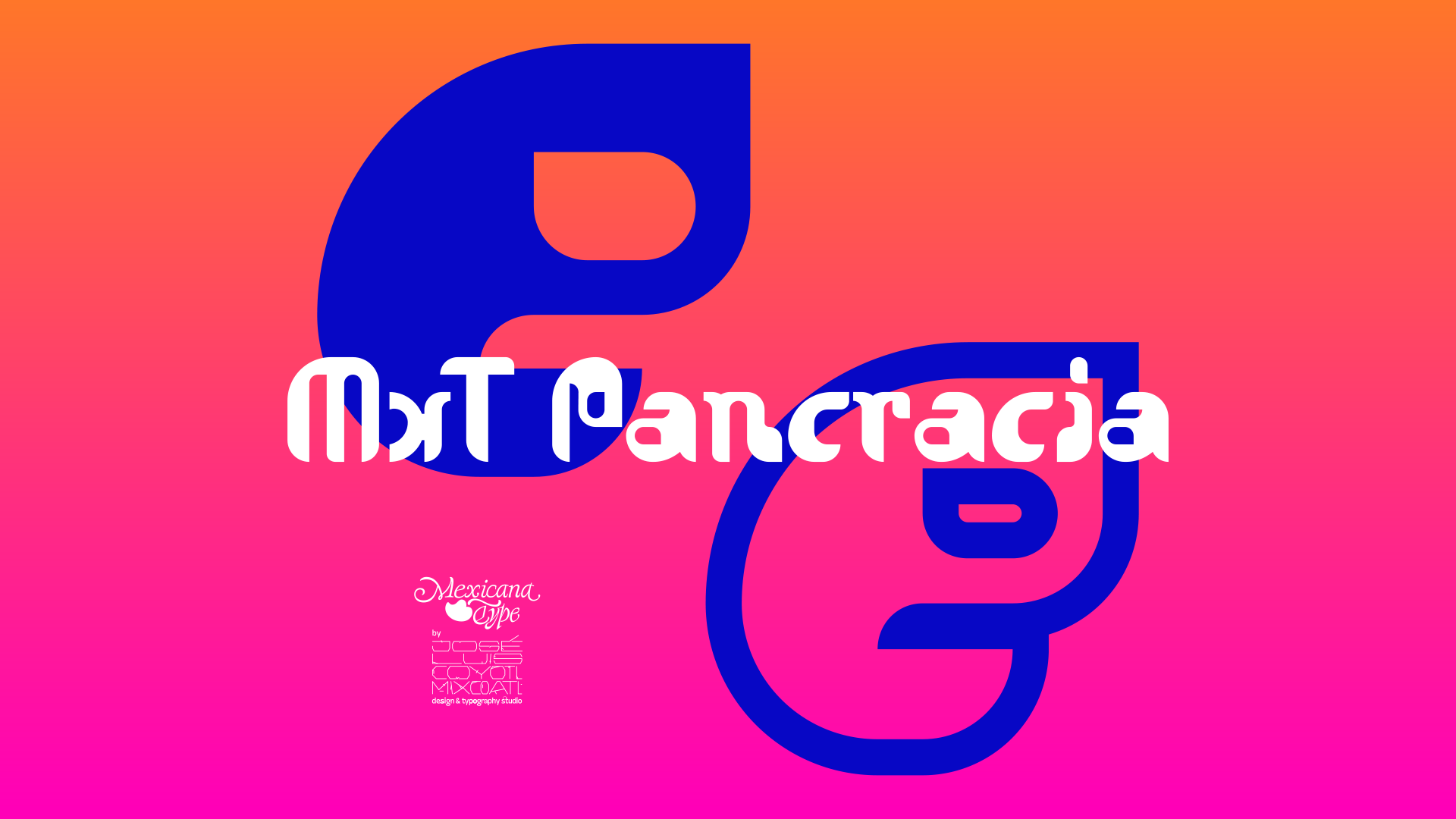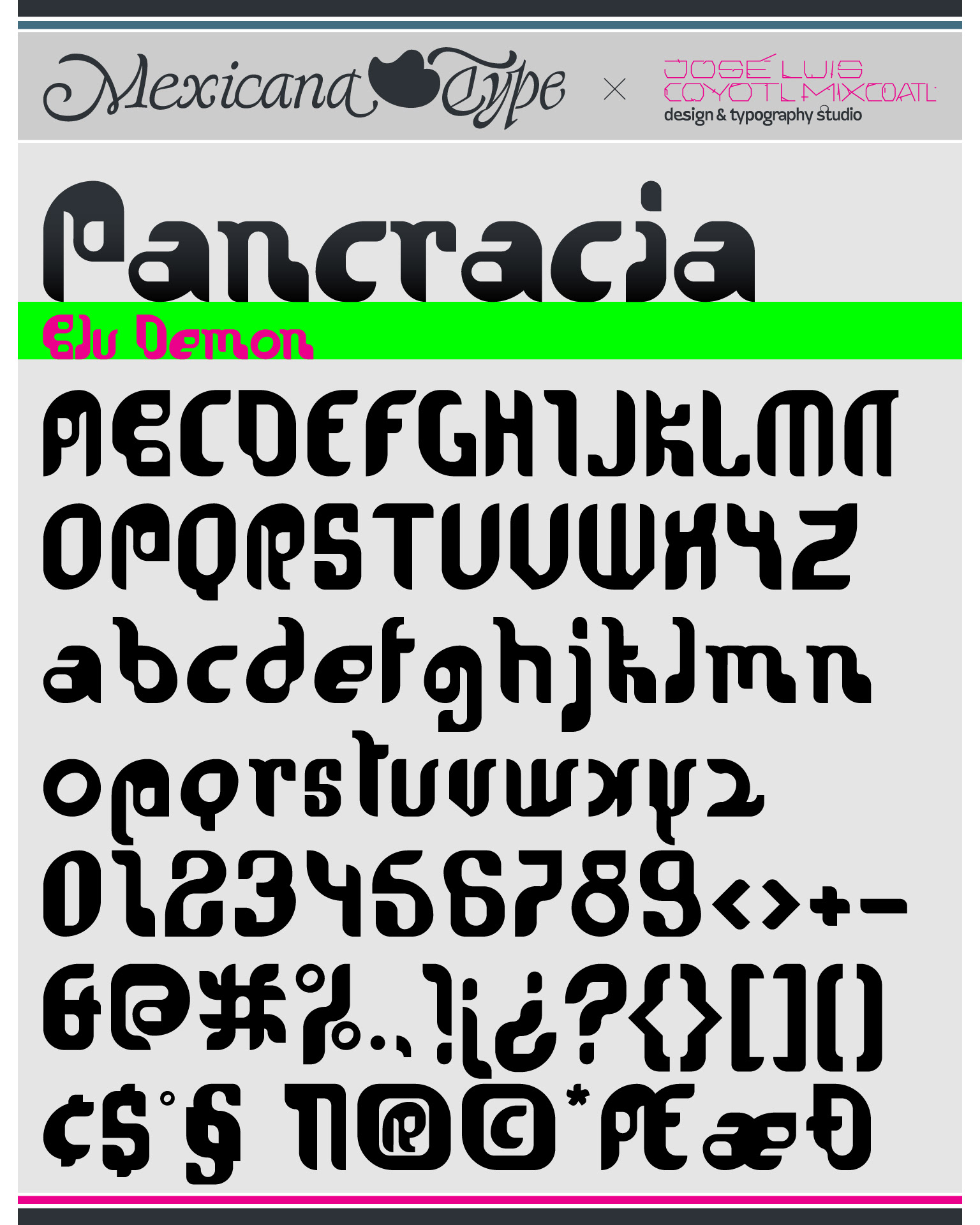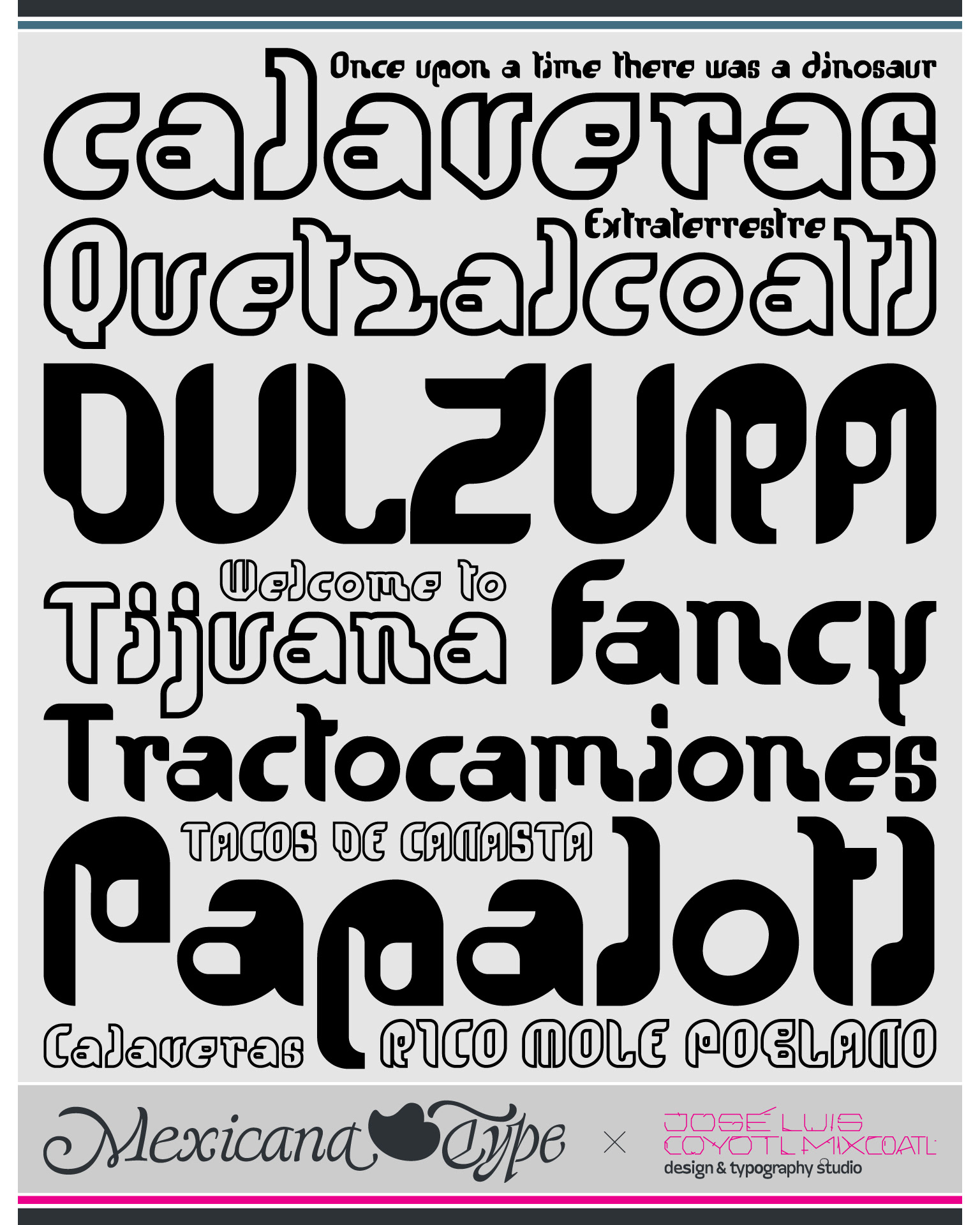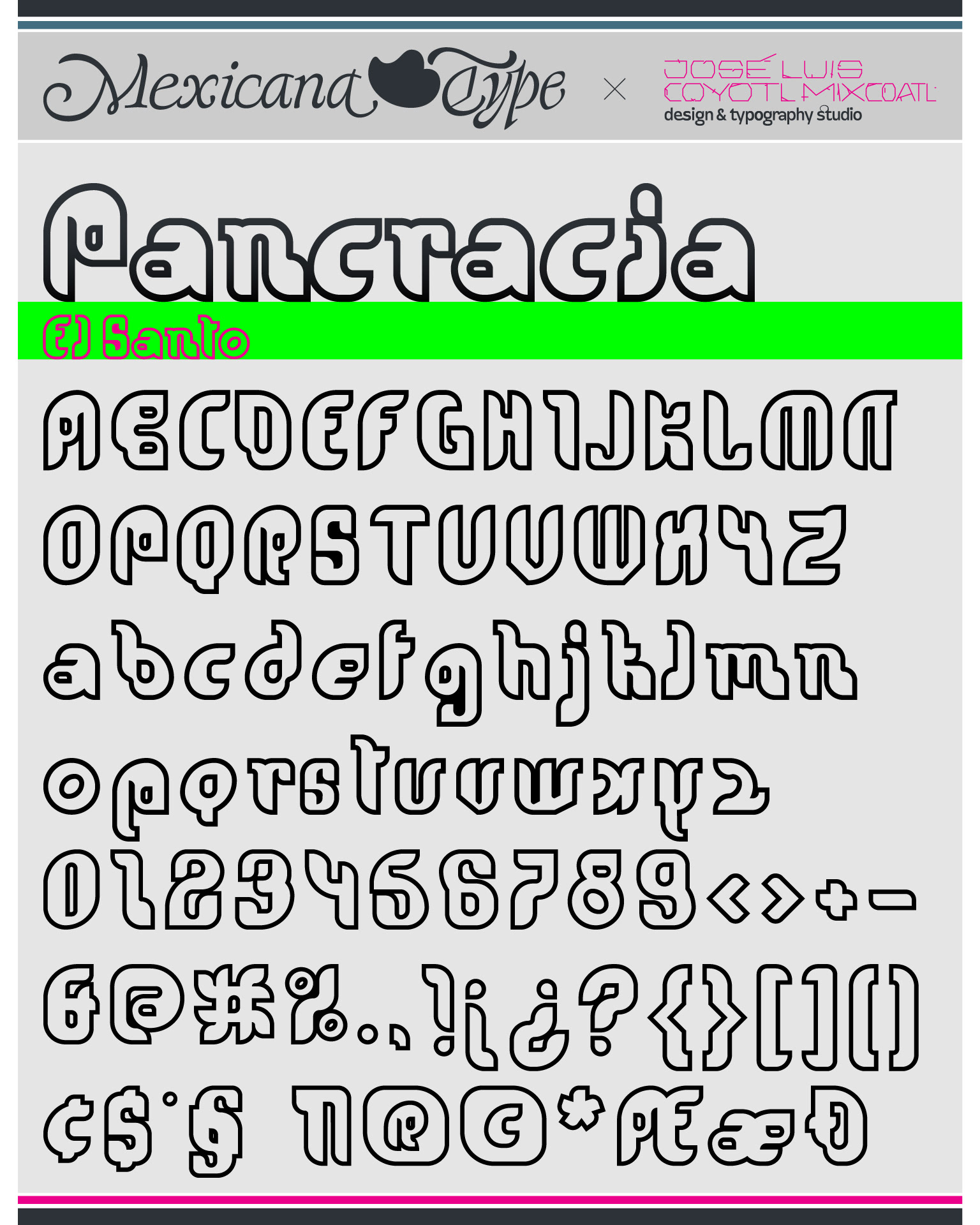
MxT Pancracia nace de la exploración iconográfica y como fenómeno cultural de la lucha libre, siendo ésta una de las expresiones más representativas de la cultura popular mexicana, por lo que influenciado por la gráfica de máscaras y atuendos de luchadores, particularmente de El Santo y Blue Demon, se inspiró ésta tipografía. Con un aire vernáculo, que se rinde a la desproporción y al juego de formas modulares pero irregulares al mismo tiempo. Los caracteres de MxT Pancracia juegan a la acrobacia, a ser expresivas, a ser divertidas y juguetonas en su textura tipográfica, un poco techno y otro poco orgánica, es varias cosas a la vez. Es un experimento lúdico e iconográfico, como en las ‘e’ minúsculas se nota una forma una abstracción del perfil de las mascaritas de cada una de sus versiones: MxT Pancracia Blu Demon y MxT Pancracia El Santo.